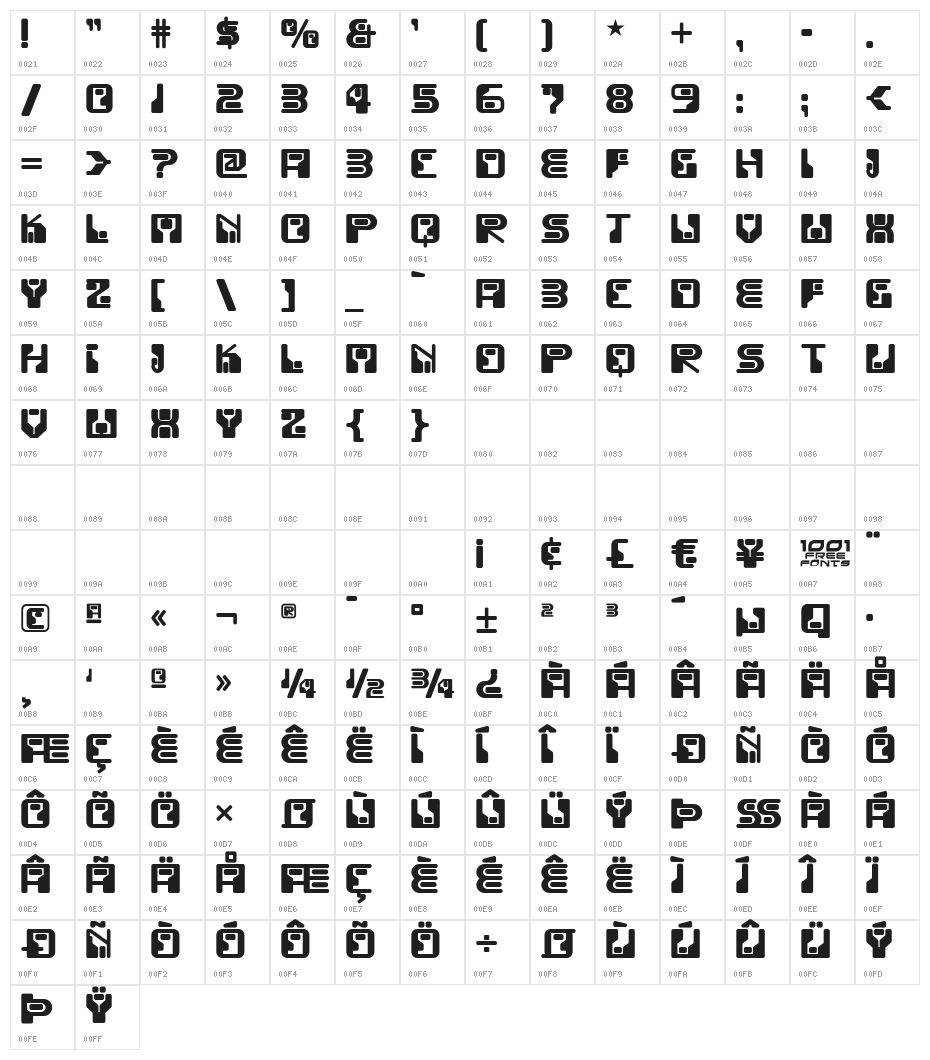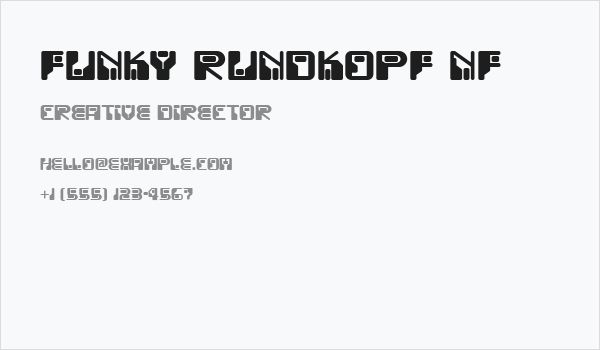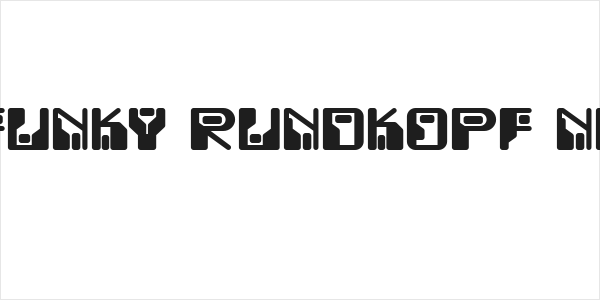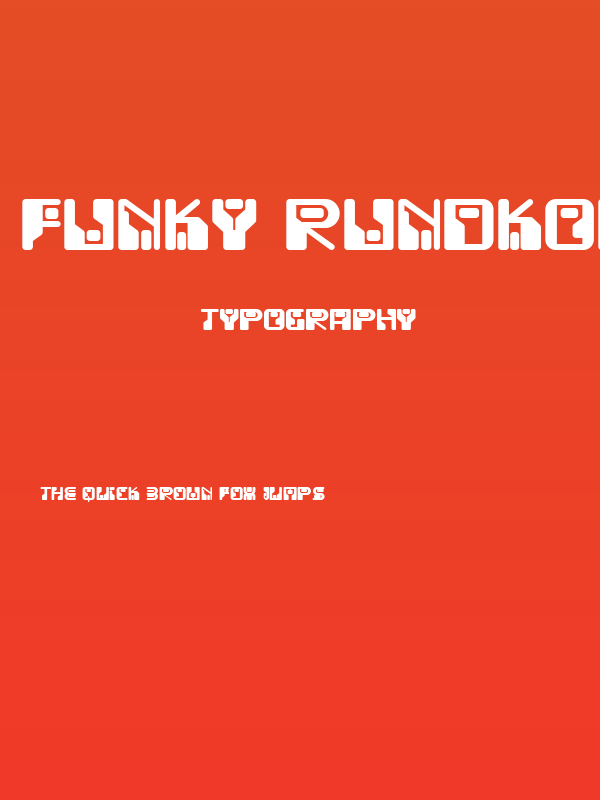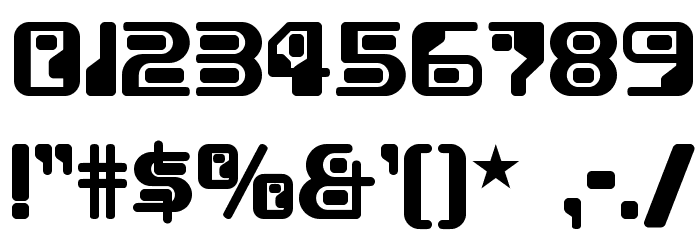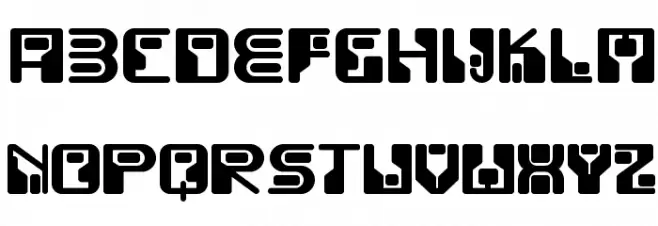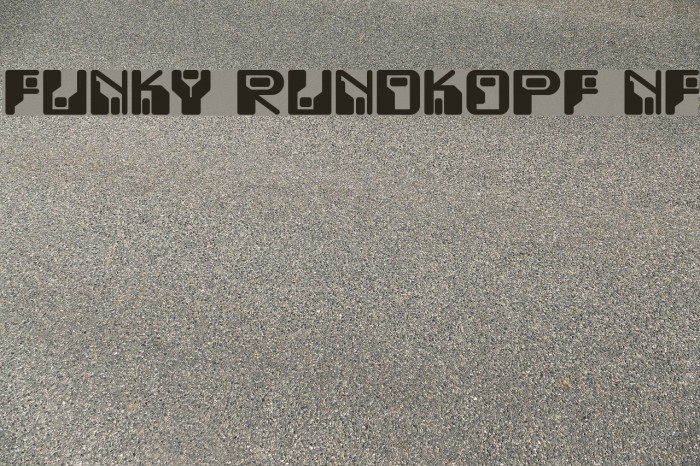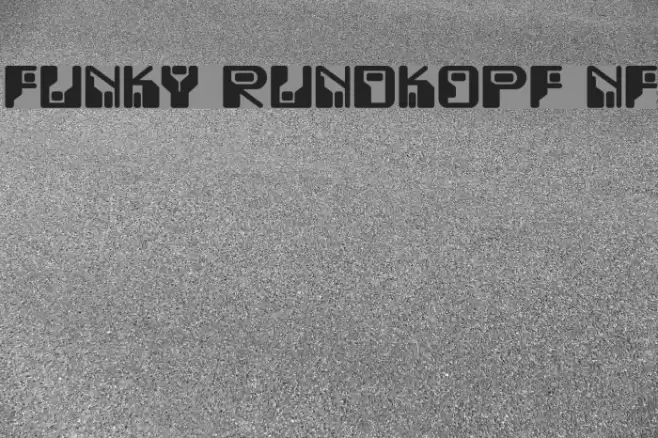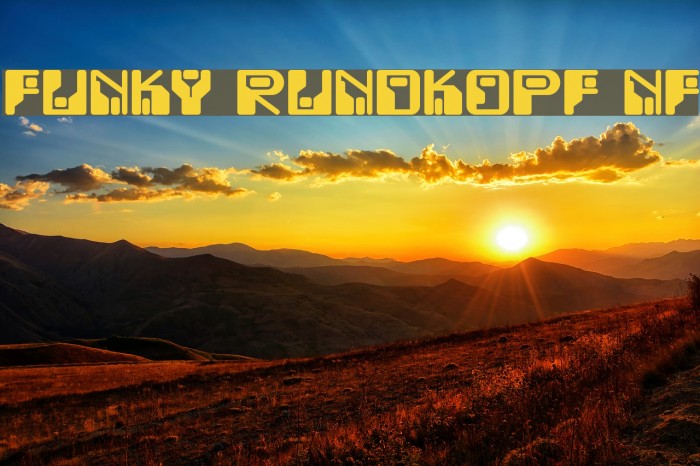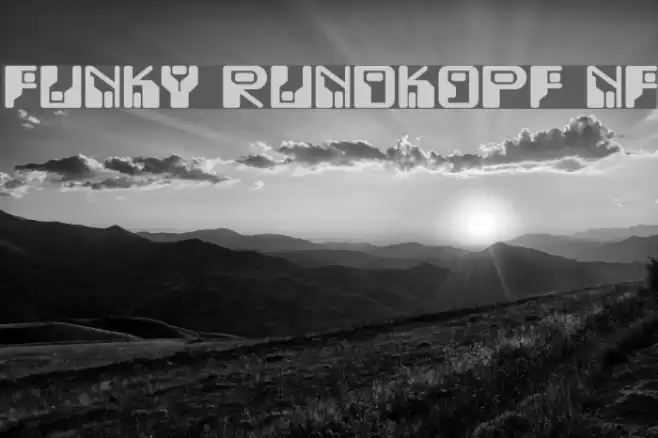
Funky Rundkopf NF Font
✎ Futuristic
| Vorgeschlagene Projekte | Ideal for projects that require a modern and playful touch, such as branding, posters, album covers, and digital media. |